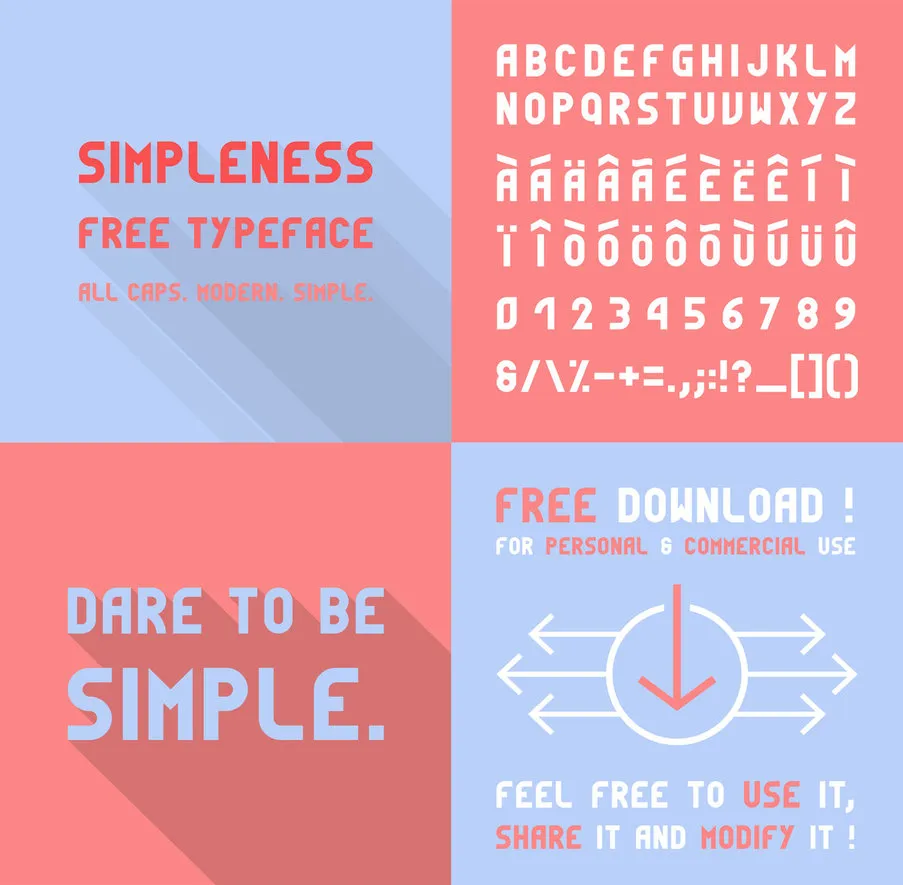
Simpleness Font – Fonte Grátis
Simpleness Font
Simpleness é uma nova adição à coleção de nossas fontes decorativas, criada pelo designer Valentin François inspirado no movimento Bauhaus. Esta all caps typeface minimalista traz um toque leve e elegante para qualquer projeto visual. Simpleness não apenas proporciona um design limpo e sofisticado, mas também oferece uma oportunidade única de explorar o potencial do uso das letras maiusculas em projetos criativos. Ideal para designers que buscam uma fonte minimalista para adicionar elegância a designs digitais, Simpleness foi concebida para ser versátil e adaptável ao longo de diversos estilos. Seja em design gráfico digital ou editoração de imagens, sua facilidade de uso e capacidades únicas o tornam uma escolha inteligente para quem busca uma fonte única que se adapta às mais diversas necessidades. Para designers experientes como vocês, Simpleness oferece a chance de explorar novas maneiras de expressar seu trabalho através da simplificação. Seu design minimalista permitirá que você destaque o conteúdo do seu projeto sem perder em elegância ou eficácia. Valentin François abraça essa ideia e está animado para ver como vocês usarão Simpleness, seja com uma tipografia de marca atraente ou para dar um toque sofisticado em designs digitais.